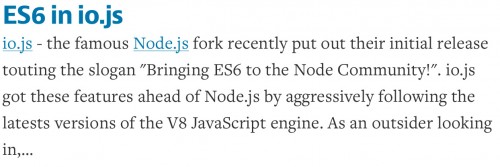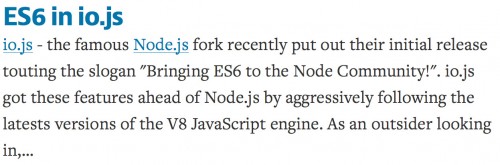
让字体显得更平滑的CSS方法
几年前我就看到过CSS里有一些属性很奇怪,当我设置这些属性或取消这些属性后,字体看起来会变得好看和不那么好看。这就是字体平滑设置的效果。我推荐大家读一下Font smoothing explained这篇文件,你会从中学到更多的关于字体平滑效果的知识,但今天这里,我只是介绍一下它们的基本用法
我对字体设计并不在行,对印刷排版也没有研究,但我知道什么字体好看,什么不好看。几年前我就看到过CSS里有一些属性很奇怪,当我设置这些属性或取消这些属性后,字体看起来会变得好看和不那么好看。这就是字体平滑设置的效果。我推荐大家读一下Font smoothing explained这篇文件,你会从中学到更多的关于字体平滑效果的知识,但今天这里,我只是介绍一下它们的基本用法:
body {
-webkit-font-smoothing: antialiased;
-moz-osx-font-smoothing: grayscale;
}
在CSS里加入这些设置和不加这些设置,区别是很微妙的:
进行平滑设置的字体效果:
Font Smoothing - With
无进行平滑设置的字体效果:
Font Smoothing - Without
区别并不是很大,但前者确实是看着更舒服,更柔和。下一次在设计你的网站显示样式时,可以尝试一下这些字体显示技术,也许会给你带来意想不到的效果!